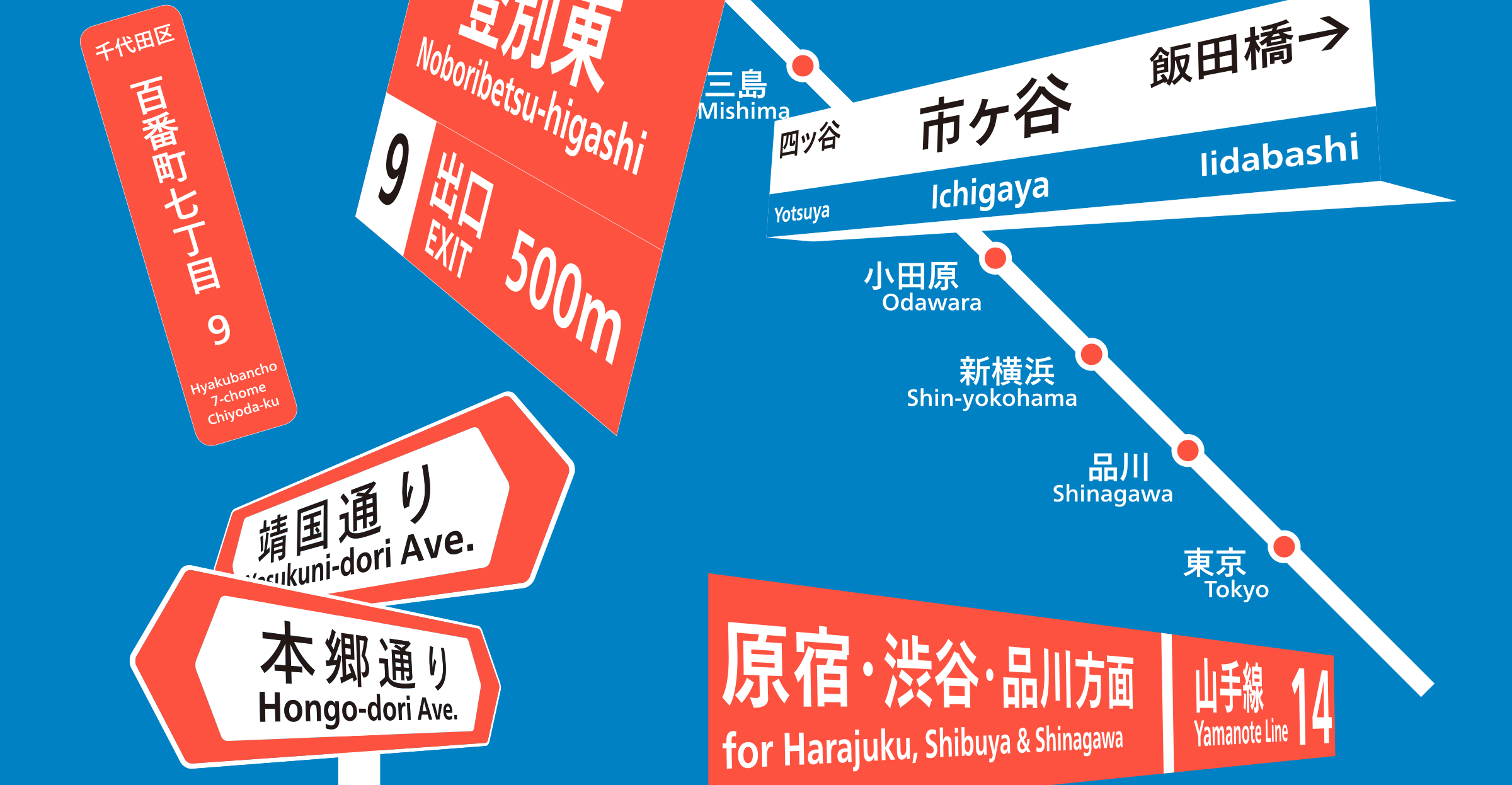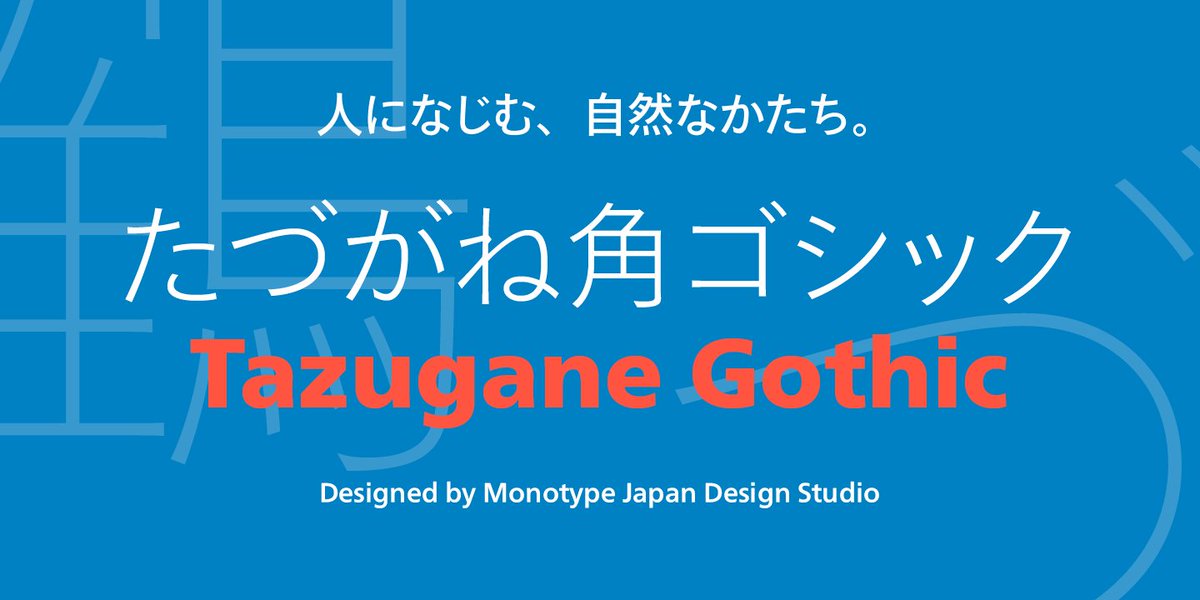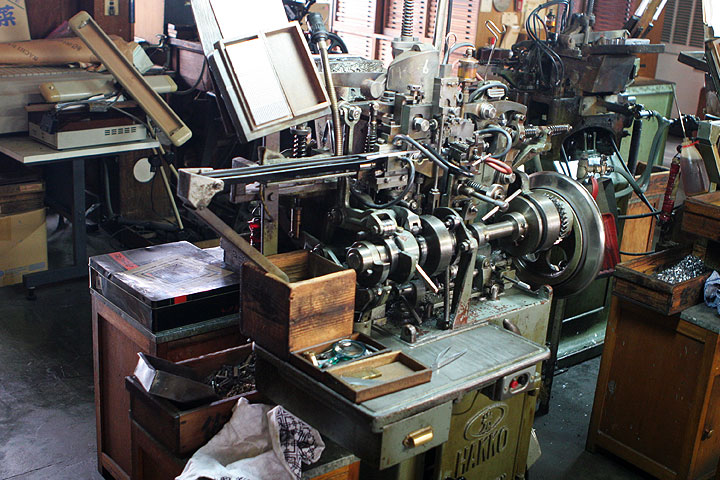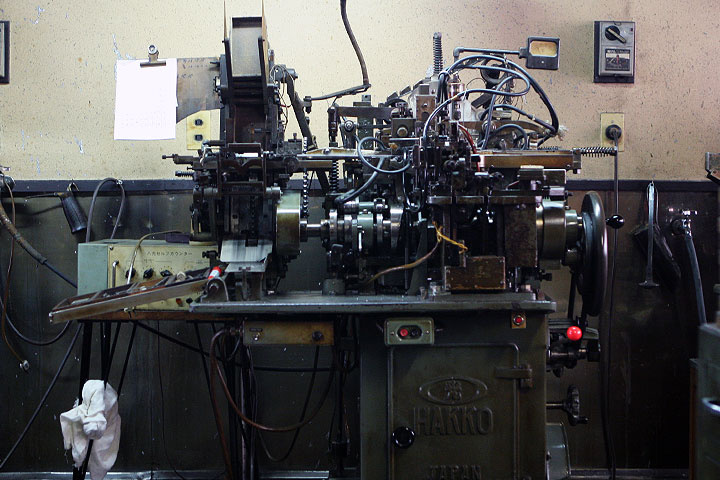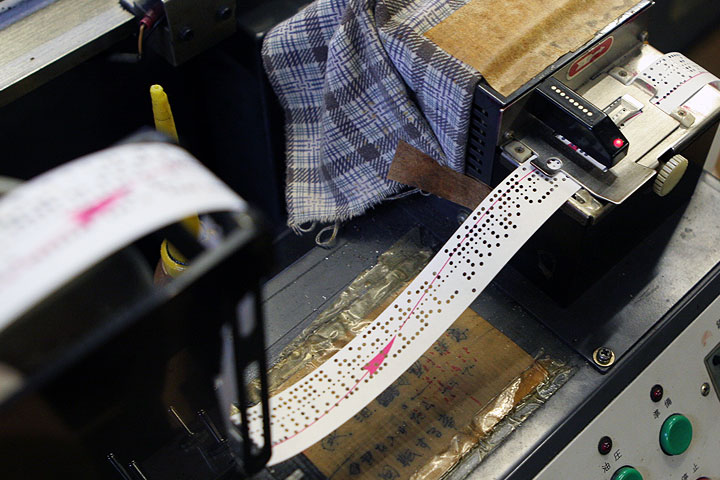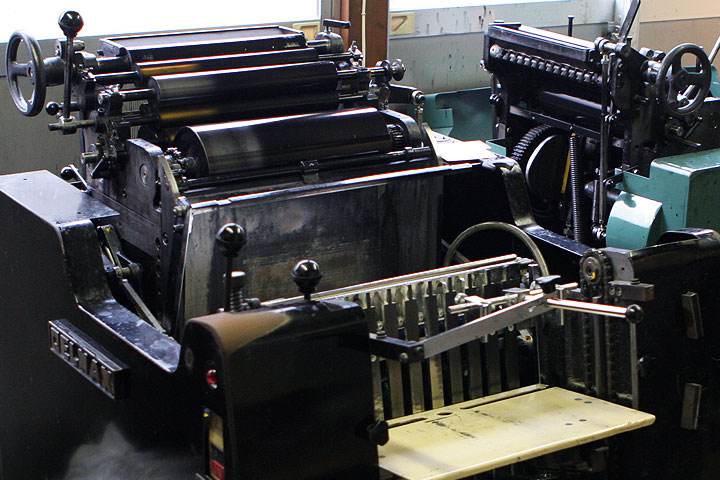
百年活字:佐佐木活字店
位于新宿榎町的活字制造贩卖所「佐佐木活字店」创办于大正六年(1917年),于去年迎来百年的佐佐木活字店至今依旧活跃在字体排印第一线,从活字铸造、捡字、排版到印刷,活字排印的完整流程都可以在这里完成,经手过的活字总数超过七百万个。此外,作为造纸公司山樱的代理店,还贩卖各类纸张,为日本的设计师提供广泛的印刷支持。我们将前往店内参观,亲眼看到沿用百年的活字铸字机、排字机和印刷机,更有机会亲手体验活版印刷。
字体前沿:Monotype Tokyo
除了体验传统的活字印刷,TypeTour 还将带领团员们了解字体设计最前沿,拜访世界最大的字体设计公司蒙纳(Monotype)的日本办公室。去年,Monotype 发布了首款原创的日文字体 Tazugane™ Gothic(たづがね™角ゴシック)。这款字体字体设计师小林章领衔,山田和宽与土井辽太合作设计完成,力图打造和经典西文字体 Neue Frutiger 一样的「安心感」。我们将造访位于东京千代田区的办公室,设计师土井辽太将给我们讲述 Tazugane 的设计故事,以及最新字体设计软件 Glyphs 的经验之谈,届时团员们可以准备问题,和土井作现场交流。